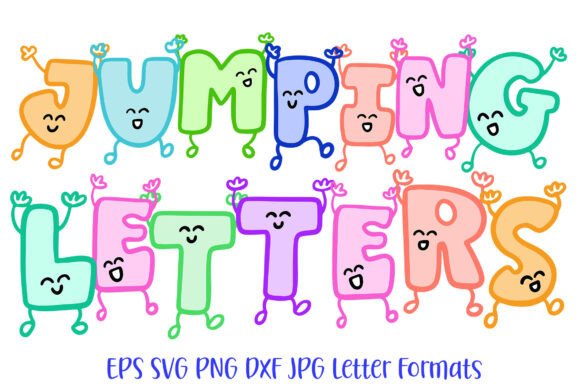
Jumping Letters Font Doodle Lettering
์ •๋ฐ€ํ•˜๊ฒŒ ์ œ์ž‘๋œ Jumping Letters Font Doodle Lettering๋Š” ๊น”๋”ํ•œ ๋ฒกํ„ฐ, ๋ถ€๋“œ๋Ÿฌ์šด ํƒ€์ดํฌ๊ทธ๋ž˜ํ”ผ ๋ฐ ์•ˆ์‹ฌํ•  ์ˆ˜ ์žˆ๋Š” ์ƒ์—…์šฉ ๋ผ์ด์„ ์Šค๋ฅผ ์ œ๊ณตํ•ฉ๋‹ˆ๋‹ค.